米国 Monotype Imaging Inc.の日本法人Monotype株式会社(東京都港区、以下 Monotype)は、日本のタイプファウンダリであるエヌアイシィ株式会社(NIS Font)と提携。Monotypeの提供するフォントサービス「Monotype Fonts」「MyFonts」に計127書体の提供を開始しました。
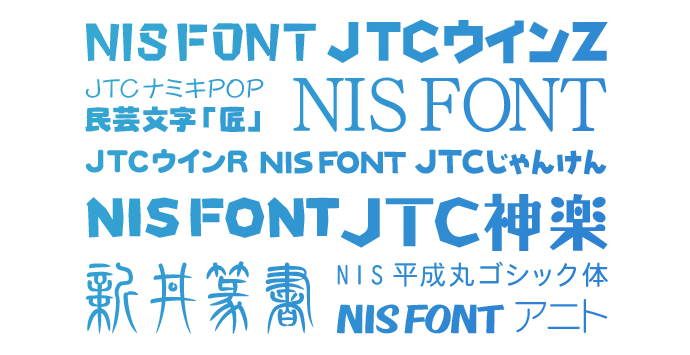
NIS Fontは伝えたい想いをフォントとして
「より楽しく、より美しく」いつの時代にもお届けします。
NIS Fontのご紹介 当社は1980年、日本情報科学株式会社として設立され、初期のパーソナルコンピュータに付属するアウトラインフォントを独自開発することから始まりました。一般ユーザー向け製品が登場するにつれ、英語社名「Nippon Information Science」の頭文字から「NIS Font」の名称が生まれました。 |
S明朝シリーズ
「柔らかなイメージと自然さ」をコンセプトにしたベーシックなフォルムです。文字の運びとかたちを大切にしているため、キャッチフレーズからボディコピー、エディトリアルなど、広告・雑誌、デザインをはじめ、幅広い分野でお使いいただけます。
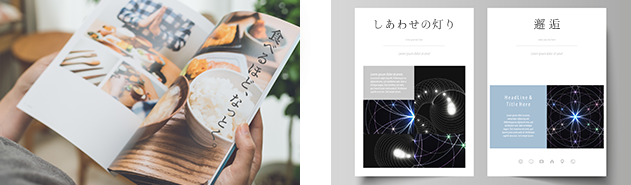
NIS_UDゴシックシリーズ
どなたにも親しみやすい、クセのないフォーマル(基本)な書体です。デザイン性を全面に押し出し過ぎることなく、あらゆる場所や媒体での利用において、視認性・判読性が高く、読み手にとってより自然で優しいフォントに仕上げています。
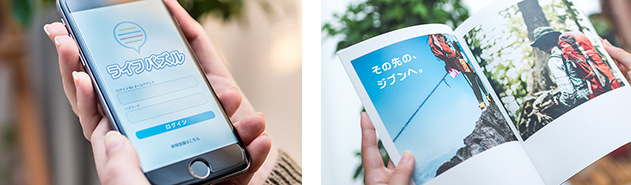
JTCウインZシリーズ
100%直線のみで構成された、NIS Fontのなかでも人気を誇るゴシック体です。直線が持つ力強さを備えながらも、すっきりと見えるデザインはJTCウインZならでは。機械に頼らず手書きデザインですべてつくられた、デザイナー定番フォントです。
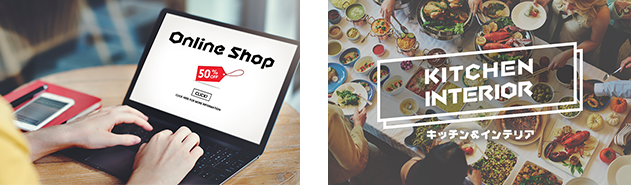
ウインクスL+JTCウインSシリーズ
「横組みに適した“かな“」をコンセプトにした横組み専用のフォルムです。漢字とかなの横と縦のラインが美しくそろうため、番組テロップやPOPチラシにも最適。
太さ(ウエイト)のバリエーション(ファミリーフォント)を4種類ご用意しています。
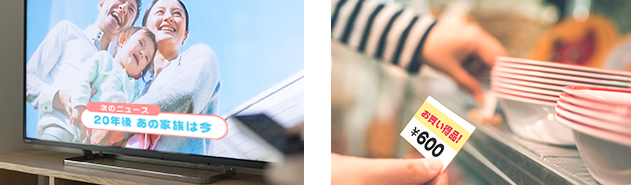
オススメ書体
NIS Fontは様々な媒体で活用されております。文字の美しさを最も表現できるフォントです。数書体をピックアップした使用イメージの参考となるフォントをご紹介いたします。
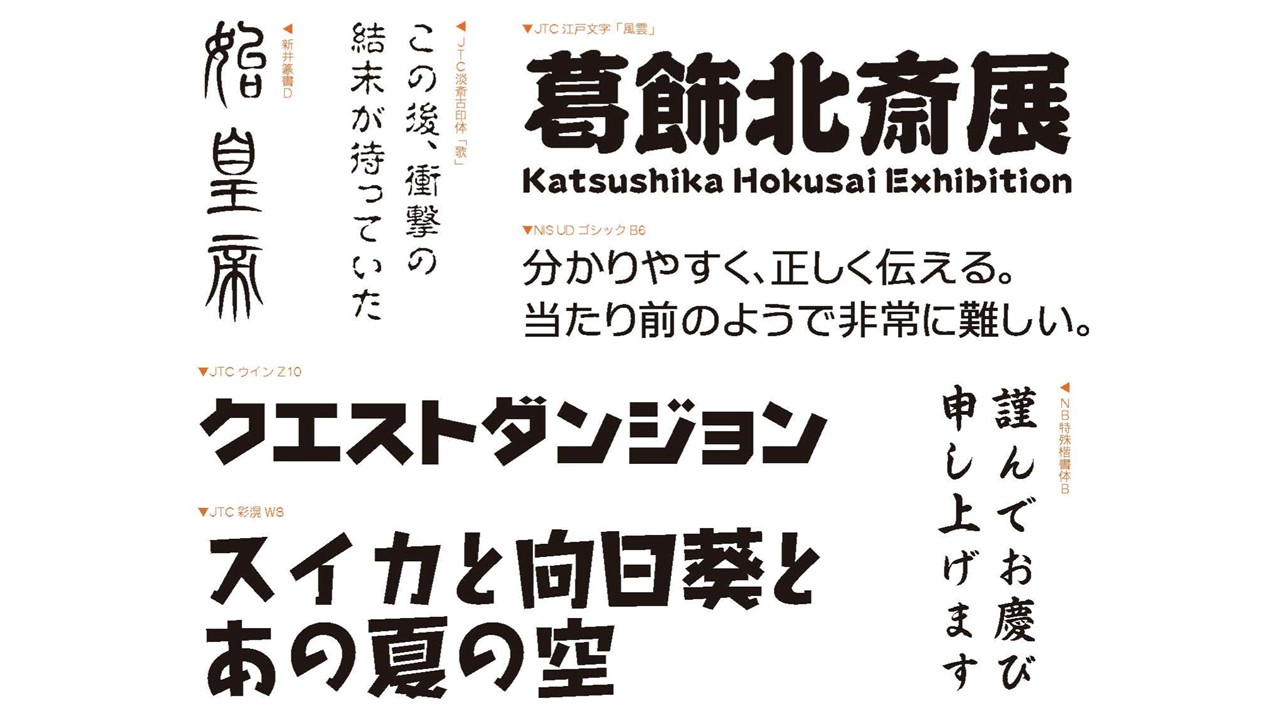
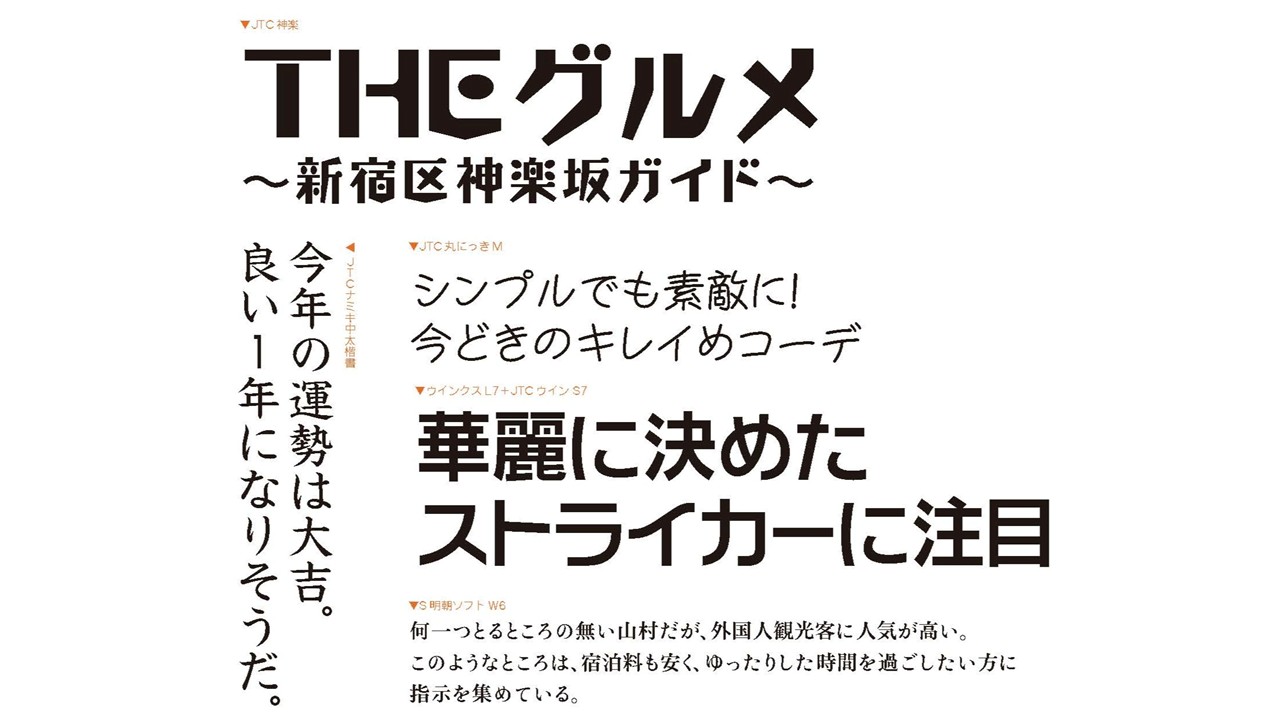
| 新井行明 | M | 筆系 |
| 新井篆書 | D / R / S | 専門書系 |
| JTC淡斎行書「彩」 | L | 筆系 |
| JTCカル | 2 / 3 | ゴシック系 |
| JTC淡斎篆書「吟」 | L | 筆系 |
| 堀明朝 | L | 明朝系 |
| JTC淡斎草書「濃」 | L | 筆系 |
| JTC淡斎古印体行書「舞」 | L | 筆系 |
| 仙草 | L | 手書き系 |
| JTC淡斎古印体「歌」 | R / B | 筆系 |
| JTCわりばし | H | デザイン系 |
| ポルA体 | UL / UB | デザイン系 |
| アニト | L | ゴシック系 |
| セイビ楷書 | L | 筆系 |
| コミクスM+S | UL / R /B | その他 |
| JTC江戸文字「風雲」 | UB | 筆系 |
| JTCフリー行書 | R | 筆系 |
| NIS平成角ゴシック体 | W3 / W9 | ゴシック系 |
| ウインクスJ+M | M1 / M5 / M9 | 明朝系 |
| JTCじゃんけん | M / UB | デザイン系 |
| JTC神楽 | UB | デザイン系 |
| 曲水 | R / B / L | 筆系 |
| JTCナミキ教科書体 | R | 専門書系 |
| JTCウインM | M1 / M3 / M5 / M7 M8 / M9 / M10 | 明朝系 |
| ミックスプラスM | M1 / M3 / M5 / M7 M8 / M9 / M10 | その他 |
| ミックスプラスS | S1 / S3 / S4 / S6 S7 / S8 / S10 | その他 |
| NB特殊楷書体 | M / B | 筆系 |
| JTCナミキ特太楷書 | B | 筆系 |
| JTCナミキ中太楷書 | R | 筆系 |
| ネオ勘 | UB | 筆系 |
| JTCにっき | L | 手書き系 |
| JTC丸にっき | UL / R / M / L DB / B | 手書き系 |
| JTCにっき丸ペン | L | 手書き系 |
| JTCナミキPOP | L / M / UB | デザイン系 |
| NIS-POP文字 | UB | デザイン系 |
| JTCウインR | R1/ R4 / R7 / R8 / R10 | 丸ゴシック系 |
| JTCウインS | S1 / S3 / S4 / S6 S7 / S8 / S10 | ゴシック系 |
| JTC彩滉 | B | デザイン系 |
| S明朝ハード | W3 / W4 / W5 / W6 / W7 / W8/ W9 | 明朝系 |
| S明朝ソフト | W3 / W4 / W5 / W6 / W7 / W8/ W9 | 明朝系 |
| JTC民芸文字「匠」 | H | デザイン系 |
| NIS_UDゴシックB | L / R / DB | UD |
| NIS_UDゴシックD | L / R / DB / EB | UD |
| ウインクスV+M | UL / M / UB | 明朝系 |
| ウインクスL+S | UL / R / B / H | ゴシック系 |
| ウインクスS+S | UL / R / B / H | ゴシック系 |
| JTCウインZ | UL / M / H | デザイン系 |
| JTCウインZM | UB | デザイン系 |
| JTC直線江戸文字「剣」 | H | デザイン系 |